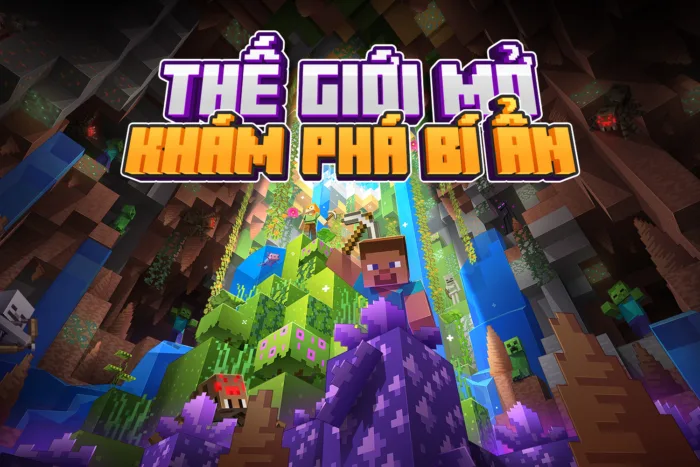
DVN Minercraftory Việt hóa – Font chữ của game Mine Craft bản chuẩn
DVN Minercraftory Việt hóa là một font chữ lấy cảm hứng từ phong cách pixel, đậm chất game Minecraft. Với các đường nét vuông vức, mạnh mẽ, font này phù hợp để thiết kế tiêu đề, banner, logo hoặc các dự án liên quan đến game, công nghệ, và thế giới ảo.
Phiên bản này đã được Việt hóa được tối ưu hóa để hỗ trợ đầy đủ bảng chữ cái tiếng Việt, bao gồm dấu và ký tự đặc biệt, giúp người dùng dễ dàng sử dụng trong các thiết kế mang đậm bản sắc Việt. Các ký tự được điều chỉnh để giữ nguyên phong cách pixel đặc trưng mà vẫn đảm bảo tính dễ đọc.
DVN Minercraftory là lựa chọn lý tưởng cho những ai muốn tạo ra các thiết kế mang phong cách retro, game 8-bit hoặc các nội dung sáng tạo về thế giới số. Font này không chỉ giúp dự án của bạn nổi bật mà còn mang đến sự hoài niệm và cá tính độc đáo.